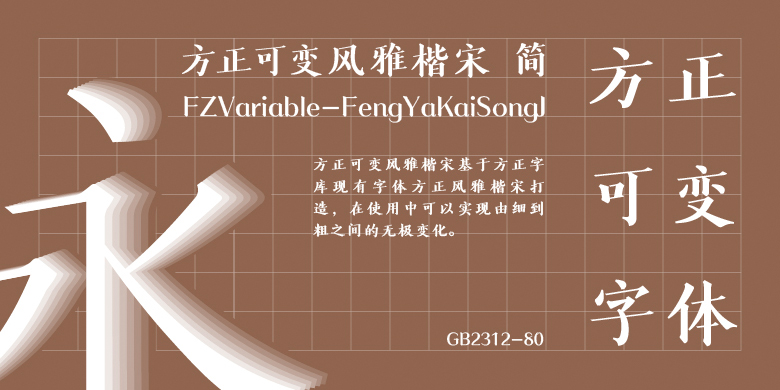
字体名称: 方正可变风雅楷
方正可变风雅楷宋 简
方正可变风雅楷宋字体支持文字粗细无级调节,设计师通过调整字重轴(Weight)的变化,可以实现字形的平滑连续的细微调整,满足不同版式的设计需求。 方正风雅楷宋融合了楷体和宋体的特征,既有楷体的书写感,又有宋体的设计感。创作者根据传统书法的运笔法则和对当代设计的理解,试图让整套字体具备一定的灵动性。这款字体富有人文气息,给人以画般美感,是创作者深究古人书法法度所获心得,有天质自然之美。方正风雅楷宋家族有6款不同的字重,适用于带有清和雅致风格的标题和正文排版,粗字重的还适用于广告、标志和产品包装的设计。